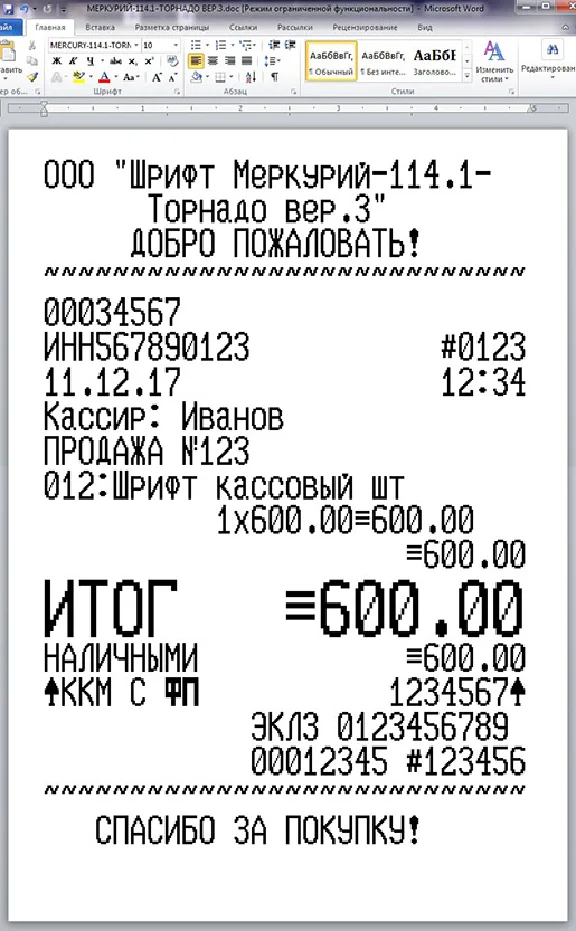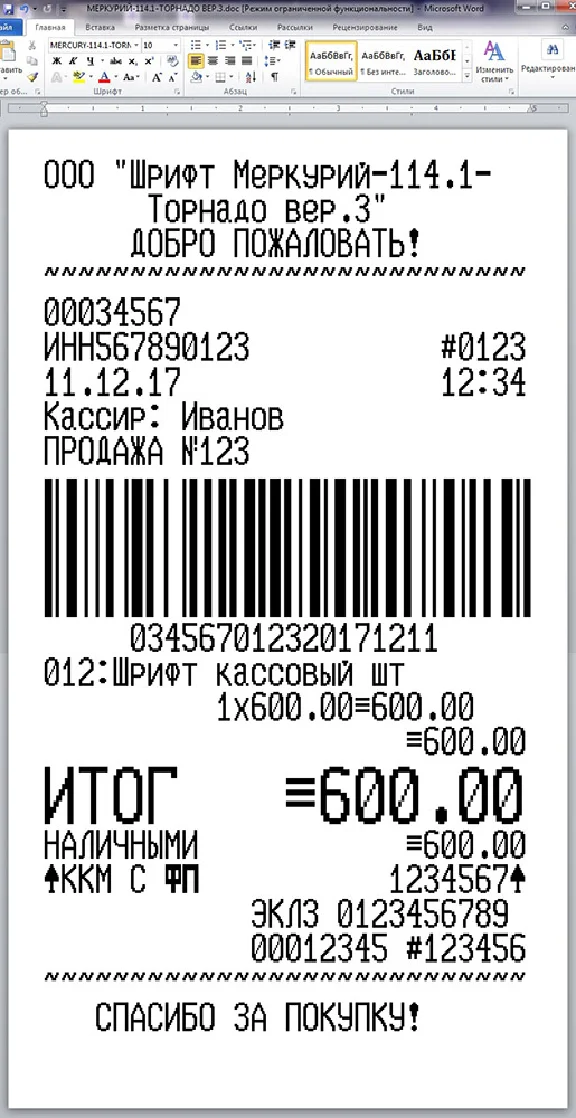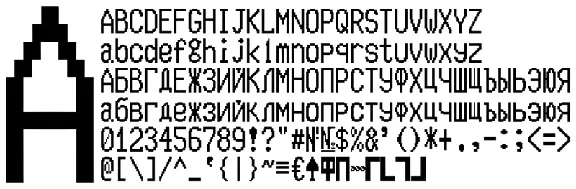
Шрифт кассового аппарата МЕРКУРИЙ-114.1-ТОРНАДО (Версия матрицы 16х20) в формате TTF (русские и английские буквы) для использования в программе Microsoft Word. В архиве находятся шрифт в формате TTF и шаблон чека. Вам остается только установить шрифт в систему (обычно C:\WINDOWS\Fonts), открыть шаблон и начать редактирование. Печатать чеки предпочтительно на термопринтере, на кассовой термоленте. Хотя можно печатать и на струйнике и лазерном, с возможностью вывода на факсовую бумагу. Лучшее качество, естественно, при печати на термопринтерах.